Setiap jenis font bisa mencerminkan karakter merek karena memiliki gaya huruf yang berbeda, dan bisa mencerminkan jenis brand yang berbeda. Sebuah brand bisa menggunakan berbagai gaya font yang bisa disesuaikan karakter brand, jenis bisnis dan pesan branding. Gaya font script yang alami dan elegan dapat digunakan dalam berbagai desain logo bisnis yang berbeda.
Font script memiliki tampilan huruf dengan gaya alami seperti tulisan tangan, gaya huruf dapat memiliki tampilan huruf latin dan bukan. Guratan garis yang alami seperti tulisan tangan menciptakan tampilan yang menarik dan unik. Terkadang font script bisa tampil alami, elegan dan ramah, bergantung ketebalan dan gaya hurufnya.
CONTOH FONT SCRIPT DALAM BERBAGAI LOGO BRAND
Gaya huruf script ini menciptakan teks yang memiliki visual menarik sekaligus unik, namun harus memilih gaya huruf yang tepat agar mudah dibaca. Font script memiliki banyak variasi sehingga untuk digunakan dalam berbagai logo brand sebaiknya dipilih yang relevan dengan identitas merek. Berikut ini beberapa contoh berbagai logo brand yang menggunakan font script yang menarik:
Font Script dalam Logo Homestay atau Hotel
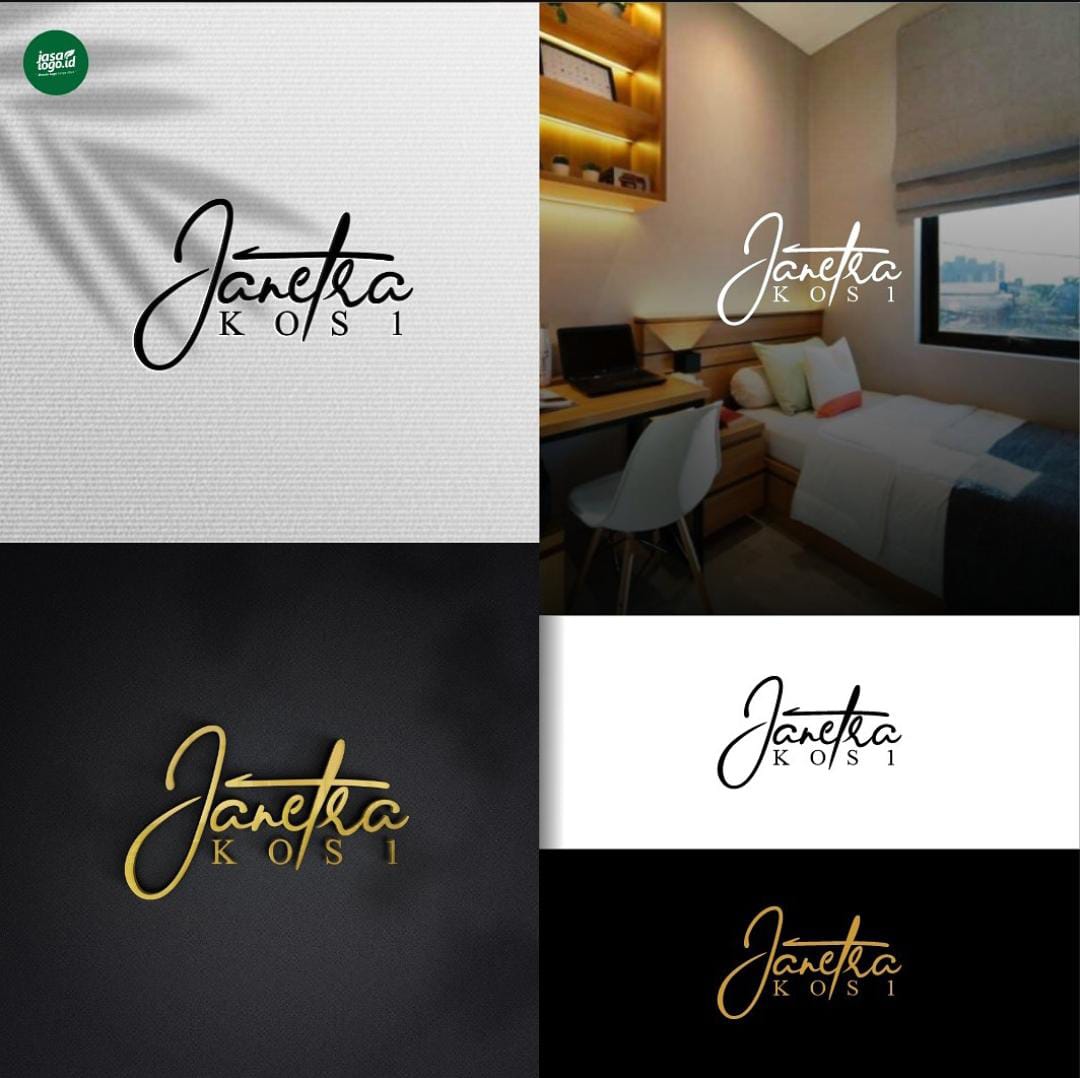
Gaya huruf script seringkali tampil elegan terutama yang menggunakan garis huruf yang tipis dan memiliki garis-garis elegan. Font yang tampil elegan ini akan menciptakan brand yang mewah dan premium. Tak heran jika digunakan untuk desain logo hotel, Homestay atau kos-kosan.
Logo hotel akan tampil elegan dan berkesan mewah, sehingga bisa mencerminkan jika hotel berkualitas. Gaya huruf script yang elegan akan cukup relevan dengan citra brand hotel yang mewah.
Dalam logo tersebut font script terlihat sederhana dan masih mudah terbaca, gaya huruf miring membuat logo terlihat semakin elegan. Kombinasi font script dan serif tersebut menciptakan desain logo yang elegan dan mewah.
Font Script dalam Logo Interior
Gaya huruf yang alami ini sering dipilih yang memiliki huruf tipis sehingga menciptakan tampilan elegan. Pada bisnis terkait interior atau perumahan, gaya script yang elegan juga akan cocok. Font script bisa mencerminkan kesan ramah, nyaman dan elegan, sehingga meningkatkan kepercayaan audiens.
Seringkali font script digunakan dalam berbagai brand dengan jenis logo wordmark, yang mengutamakan teks nama merek. Pada logo tersebut teks nama merek dikombinasikan dengan gambar atap sehingga terlihat menarik.
Font script yang digunakan memiliki gaya alami tetapi elegan sehingga menciptakan logo yang berkesan mewah atau premium. Gaya huruf tersebut membuat brand atau bisnis terlihat dapat dipercaya karena berkesan mewah.
Font Script dalam Logo Perawatan dan Spa
Logo yang menggunakan nama bisnis dengan lengkap akan cocok menggunakan font script daripada inisial. Teks nama bisnis akan terbaca dengan baik dan mencerminkan karakter brand yang elegan. Bisnis perawatan dan spa memiliki citra elegan dan feminim, sehingga cocok dengan font script yang elegan.
Garis-garis huruf pada logo tersebut terlihat halus dan bersih, tidak berantakan seperti tulisan tangan sehingga tampil lebih elegan. Ikon logo yang juga memiliki desain gambar elegan terlihat harmonis dengan font script yang elegan. Gaya script yang digunakan pada logo spa tersebut bisa mencerminkan citra brand yang elegan dan feminim.
Font Script dalam Logo Minuman
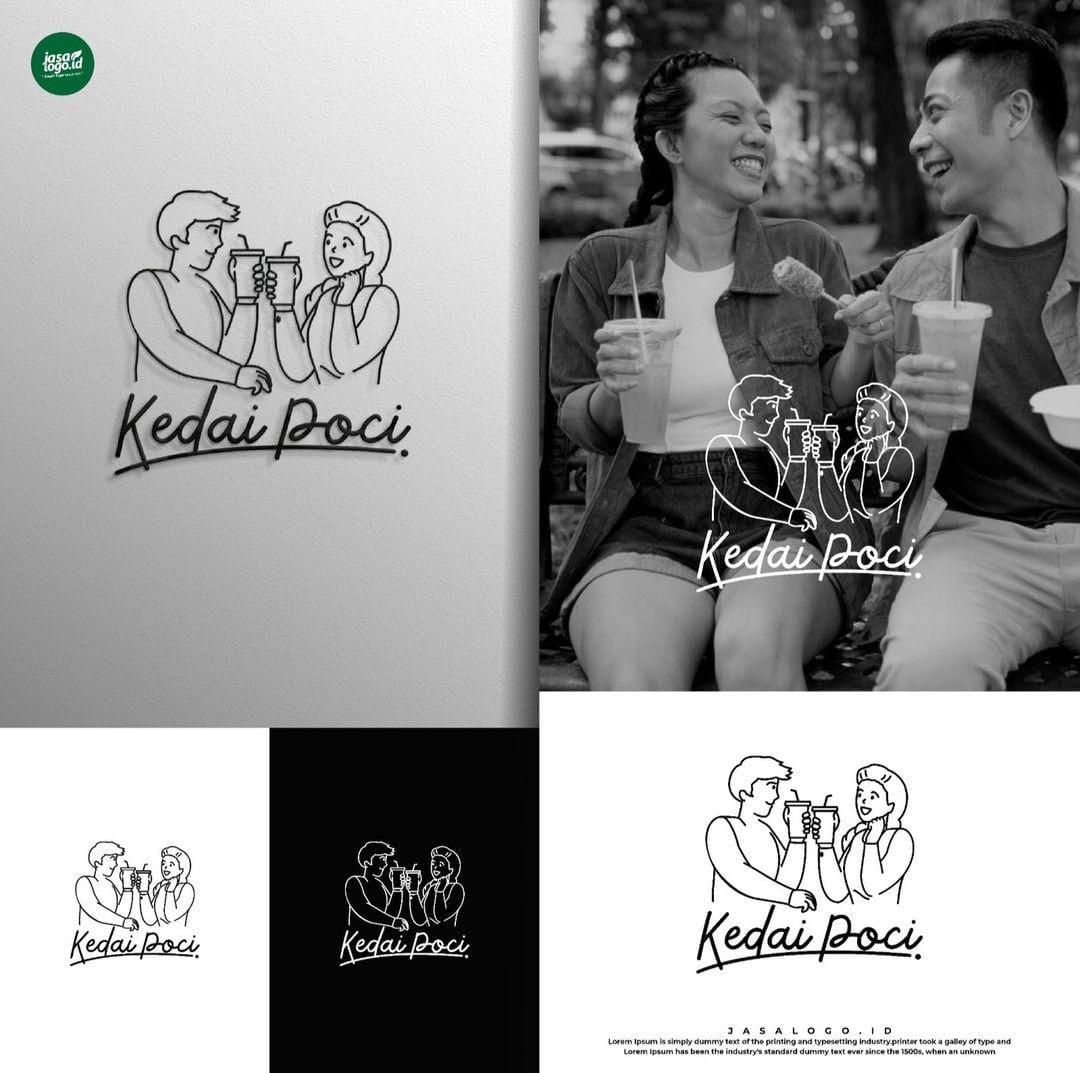
Gaya huruf script yang memiliki huruf Latin tidak hanya menciptakan kesan elegan tetapi juga ramah dan alami. Font dengan style huruf tulisan tangan ini pada brand minuman akan tampil ramah dan estetik. Baik menggunakan gaya huruf yang bulat dan tebal atau font yang tipis bisa digunakan untuk logo minuman.
Font script pada bisnis minuman tersebut menggunakan font script latin yang tipis tapi berkesan ramah karena seperti tulisan tangan. Garis-garis huruf tidak terlalu elegan sehingga bisa menciptakan kesan ramah berkat gaya tulisan tangan. Style ikon logo line art cocok dengan penggunaan font script tipis yang tampil alami.
Font Script untuk Logo Bisnis Craft atau Kerajinan Tangan
Pada jenis bisnis terkait kerajinan tangan font script bisa mencerminkan kesan alami yang sesuai dengan citra handmade atau buatan sendiri. Font script bergaya tulisan tangan akan cocok merepresentasikan bisnis buatan tangan, sekaligus menciptakan tampilan elegan. Gaya huruf script juga bisa mencerminkan kesan kreatif dengan font script yang tipis.
Logo tersebut menggunakan jenis font script dengan gaya elegan. Kombinasi font dengan ikon gambar benang dan campur terlihat kreatif. Font tersebut terlihat seperti untaian benang sehingga mencerminkan jenis bisnis dengan baik.
Font Script dalam Logo Makanan
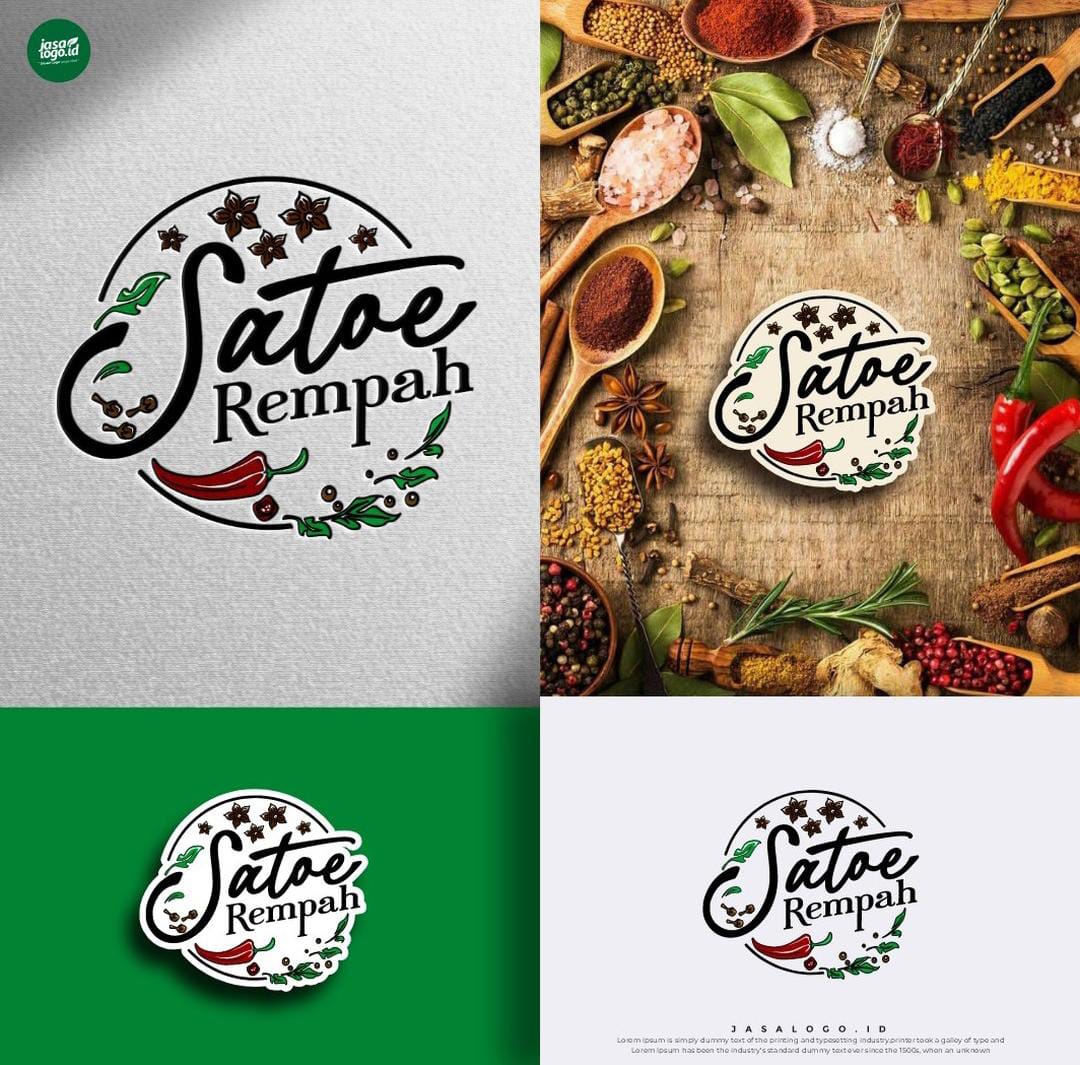
Tak hanya logo minuman, pada logo makanan penggunaan font script juga banyak ditemui. Biasanya gaya font script yang digunakan memiliki gaya huruf tebal, sudut melengkung dan bergaya bulat. Font script yang tebal akan tampil ramah dan menyenangkan, cocok untuk brand makanan.
Logo untuk bisnis makanan tersebut menggunakan font script yang agak tebal sehingga tampil ramah. Meski tebal dan memiliki huruf bersambung, namun justru keterbacaan logo sangat baik. Terkadang font yang terlalu tipis jadi sulit dibaca sehingga pada brand makanan yang sering memiliki desain ramai, cocok menggunakan font tebal.
Baca juga: Rekomendasi Warna Gelap Selain Warna Hitam untuk Desain Grafis
ALASAN MENGGUNAKAN FONT SCRIPT
Pemilihan font script yang memiliki gaya huruf alami seperti tulisan tangan pada desain logo untuk menciptakan kesan elegan, ramah dan unik. Ciri khas font yang tampil unik ini bisa sulit dibaca tetapi bisa tampil menarik. Berikut beberapa alasan mengapa font script dipilih dalam berbagai logo brand yaitu:
Mencerminkan Karakter Brand Elegan dan Berkelas
Jenis font script yang menyerupai tulisan tangan dengan garis-garis elegan akan memberikan kesan mewah, halus dan profesional. Gaya tulisan tangan dan kaligrafi yang elegan biasanya memiliki garis tipis dan elegan. Cocok untuk brand yang ingin menciptakan kesan premium seperti brand fashion high-end dan skincare mewah.
Memberikan Kesan Personal dan Hangat
Penggunaan font tulisan tangan seperti handwriting bisa menciptakan kesan lebih personal karena seperti ditulis sendiri. Font bisa mencerminkan brand yang dekat dan bergaya autentik. Gaya ini biasanya sering digunakan pada brand makanan atau minuman agar lebih dekat dengan pelanggan.
Baca juga: 7 Rekomendasi Font Untuk Brand Kecantikan
Menciptakan Nuansa Tradisional
Gaya script ini tak hanya bergaya elegan tetapi juga efektif mencerminkan nuansa tradisional. Beberapa jenis font script memiliki gaya huruf klasik, vintage dan retro. Biasanya jenis script ini memiliki gaya huruf yang panjang, melengkung dan tebal. Gaya font ini akan cocok digunakan pada jenis brand premium seperti bakery atau wine.
Menonjolkan Kreativitas dan Gaya Feminim
Dalam berbagai logo brand, font script juga berguna menciptakan kesan desain yang kreatif dan feminim. Font script sering terlihat artistik dan tampil kreatif sehingga cocok untuk mencerminkan brand yang memiliki citra kreatif dan inovatif. Gaya font script yang halus dan tipis cocok untuk mencerminkan kesan kreatif, biasanya ditemui pada logo skincare, bisnis handmade dan agensi kreatif.
Memiliki Kesan Dinamis dan Unik
Gaya font script yang memiliki garis melengkung dan huruf bersambung menciptakan kesan bergerak dan bebas. Font terlihat dinamis dan seringkali memiliki tampilan unik. Gaya ini juga bisa digunakan untuk jenis brand yang ingin tampil energik tak hanya brand elegan dan kalem saja.
Font script dalam berbagai logo brand bisa menciptakan kesan yang beragam seperti elegan, ramah, mewah hingga kreatif. Jenis brand yang berbeda bisa menggunakan gaya font script yang berbeda. Sesuaikan ketebalan, gaya huruf, dan jenis fontnya agar mencerminkan karakter dan pesan yang relevan.